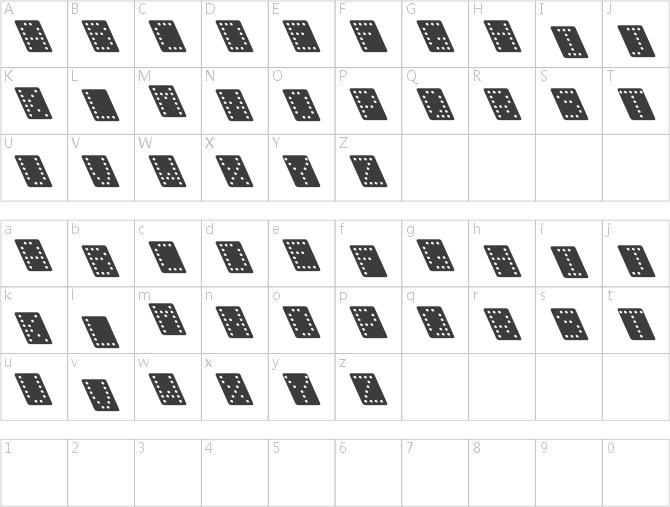
FZ BORDERS 3 LEFTY 詳情頁(yè)
FZ BORDERS 3 LEFTY字體字庫(kù)是一款讓人賞心悅目、百看不厭的英文字體,適合各類(lèi)廣告和產(chǎn)品包裝設(shè)計(jì)應(yīng)用,字體大小0.07MB,格式為ttf字體,上傳用戶(hù)是華大文化傳媒,作者/版權(quán)方為未知